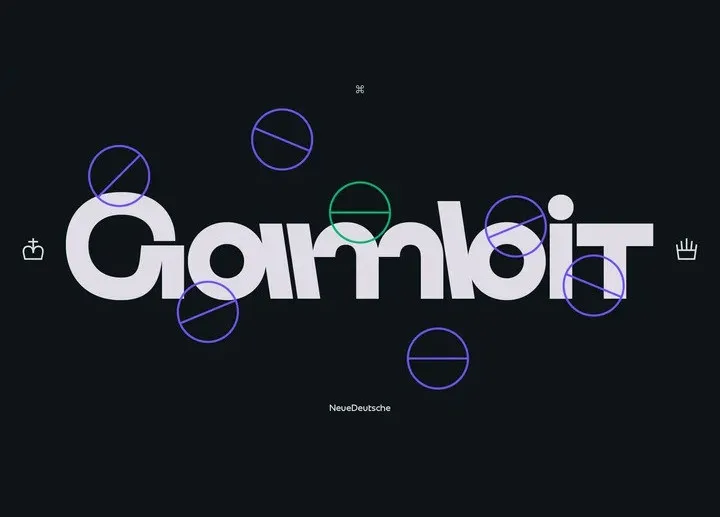
A fonte ‘Gambit Font’ é uma opção perfeita para designers que buscam simplicidade e modernidade. Essa sans serif foi projetada para oferecer um novo tom de sofisticação, com cada peso incluindo suporte linguístico extenso (Latin, Cyrillic e Grego), além de símbolos arábicos, frações, números antigas e ligaduras. A fonte ‘Gambit Font’ é ideal tanto para a criação de design gráfico quanto para projetos web corporativos e editoriais. Essa fonte, disponível em nove pesos, oferece um valor significativo. O peso regular está disponível gratuitamente, permitindo que você use sua fonte ao seu bel-prazer sem restrições. Seja qual seja o projeto, a ‘Gambit Font’ estará sempre ao seu lado para tornar as suas ideias mais sólidas e visíveis.